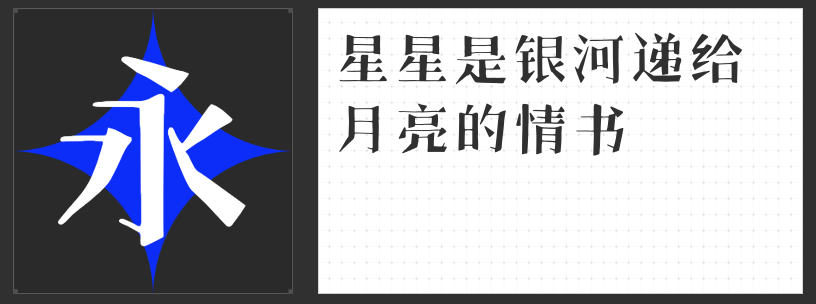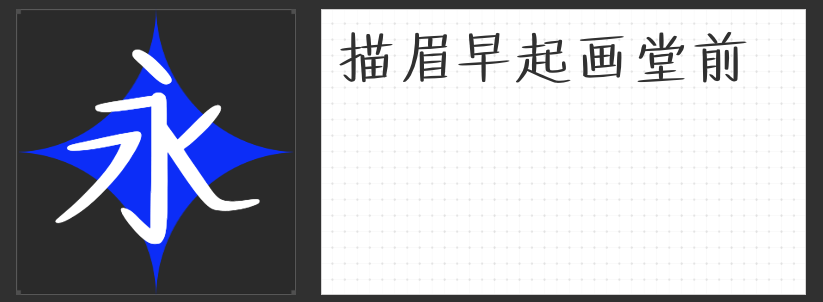
影视设计字体推荐:四款风格化字库打造视觉张力
在影视设计的视觉语言中,字体不仅是信息的载体,更是氛围营造的关键元素。从海报标题到片头字幕,从概念图到宣传物料,字体的选择直接影响作品的视觉风格与情感传递。本文精选四款风格鲜明的付费字库字体,为影视设计提供多样化的美学解决方案。
一、字恋狂灵怪简
以“笔画连带”与“几何解构”为核心设计理念,字恋狂灵怪简打破了传统字体的规整感。其折笔处被处理为三角形、菱形等几何图形,连笔流线如舞蹈般贯穿全字,赋予文字动态的视觉节奏。这种设计既保留了手写字体的自由感,又通过几何化处理强化了现代感,尤其适合奇幻、动画类影视项目的标题设计或概念艺术图,能快速传递“超现实”与“灵动”的视觉信号。
二、励字超级勇士简 常规
作为一款现代几何化黑体,励字超级勇士简以“结构严谨”与“视觉柔和”为双重要求。其笔画粗细均匀,转角处采用微弧度处理,既保留了黑体的力量感,又通过几何化设计消解了生硬感,营造出舒适、高级的视觉氛围。该字体适用于科幻、悬疑类影视的正文排版或副标题设计,能在保证信息清晰传递的同时,提升画面的整体质感。
三、高手庆科手绘宋
高手庆科手绘宋以“手写感”为基底,对传统宋体进行突破性改造:横笔画末端加入三角形装饰角,长撇笔画设计转折,钩笔画细长上挑,形成强烈的视觉对比。西文部分沿用直硬转折的直线设计,与中文风格高度统一。这种“传统与现代”的碰撞,使其既能承载历史题材影视的厚重感,又能通过趣味细节适配青春、喜剧类作品的轻松氛围,尤其适合片头字幕或概念海报。
四、字圈也字画眉楷书
字圈也字画眉楷书以“简洁乖巧”为设计核心,完全保留楷书“形体方正、笔画平直”的经典特征,同时针对现代审美优化细节:笔画粗细过渡自然,字间距与行间距经过精密调整,确保长文本阅读的舒适性。该字体是时尚杂志正文、影视剧本排版或对话字幕的理想选择,能以“无干扰”的视觉体验,让观众专注于内容本身。
这四款字体通过差异化的设计语言,覆盖了影视设计中的核心场景需求。设计师可根据项目调性,灵活选择或组合使用,以字体为媒介,强化作品的视觉叙事力。